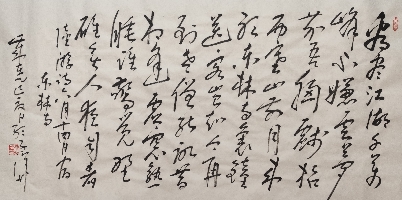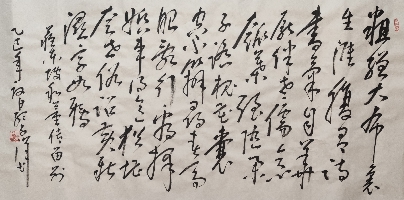
孟子洋
孟子洋简介
孟子洋又名敬宗。
山东德州人,现居北京朝阳高碑店。早年毕业于山东矿业学院,后又在中国书画函授大学书法专业毕业。
自幼酷爱书法,以写字为趣,而后以写字成癖了,历经数十年来如一日,不畏寒暑、不畏其难、孜孜不倦、笔耕不辍。习晋王羲之、颜、欧、柳、赵帖起步,锲而不舍。遍访书画界著名人士,虚心求教,早年有幸得到启功先生和任政先生的教诲和精心指点,并形成了自己的书法风格。
多年来一直致力于于右任书法的研究和两岸文化交流,并多次参加两岸书画名家文化交流活动。
2007年在北京成立了北京潭柘紫石艺术书画院。
2008年8月在北京荣宝斋与著名画家王俊松、篆刻家、书画家黄河、书法家陈振元等共同举办了书画展。
2008年12月被北京人民大会堂收藏行草书王羲之兰亭序一幅宽1.8mx长8.2m。
2008年8月为中央电视台星光大道题大字榜书(祝星光大道越办越好)。
2009年12月为中央电视台双周论坛栏目题写大字榜书(中华和谐)书法作品一幅。
2009年12月被陕西省统战部收藏8米草书长卷临怀素自叙帖一幅。台湾文联主席陆炳文、原陕西省书协主席钟明善、陕西省统战部部长周一波等参加了收藏仪式‘’
2011年在台湾台北大学与篆刻、书画家黄河、著名旅美画家陈幼白、著名书法家李海峰共同成功举办了书画展。
2011年4月22日以章草恭书4000余字的(佛教遗经)纸本八米长卷,捐赠给台湾国父纪念馆,国民党荣誉主席吴伯雄先生亲自参加了捐赠仪式。